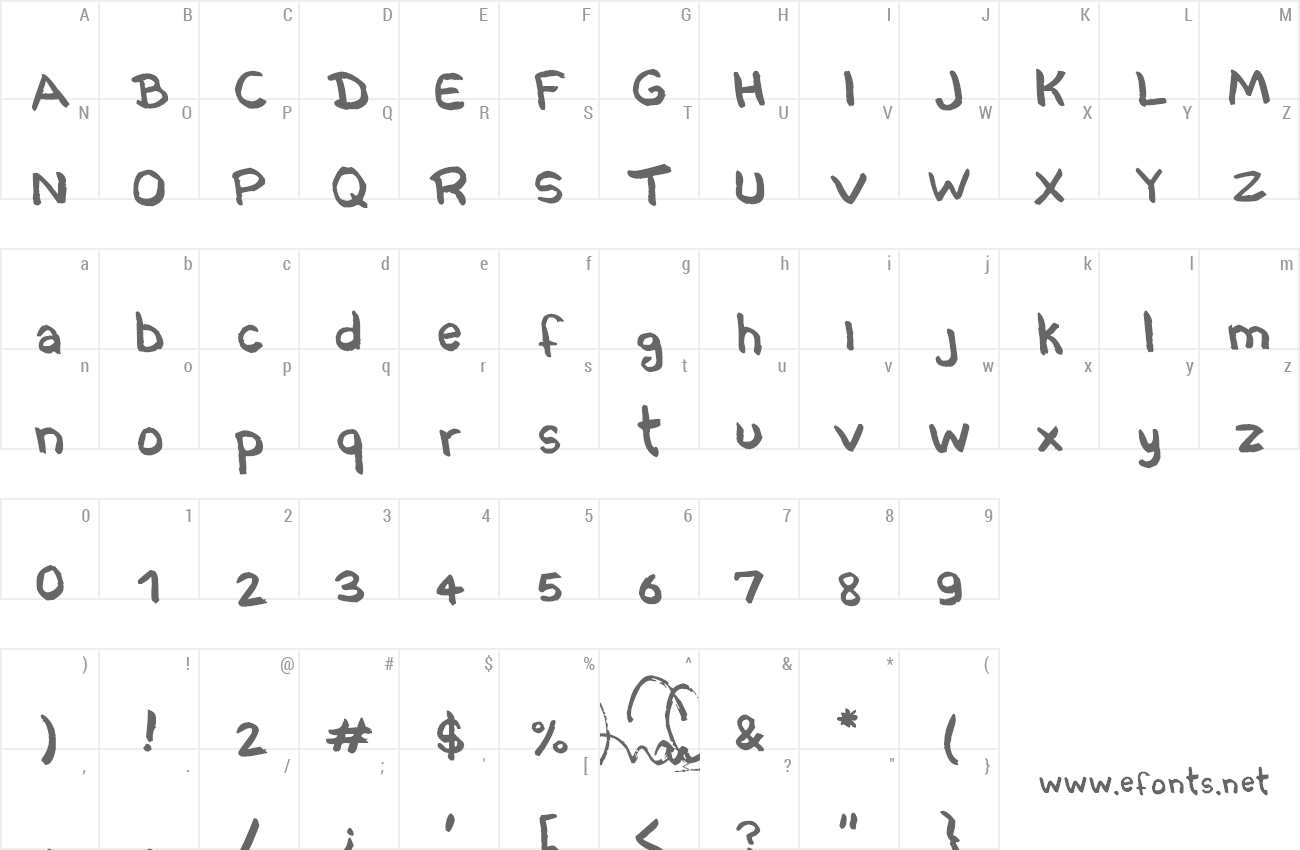
Preview and download Comix Pro 2 Font. Created by André Devaivre in Fancy Comic styles with 100% Free license.
| Font name: | Comix Pro 2 |
| Author: | André Devaivre |
| Note by André Devaivre | |
| Pour les dessinateurs de bande dessinée. Celle-ci est inspirée des phylactères de vieux albums vintage en noir et blanc des années 1930-35. Font for cartoonist. Enjoy ! |